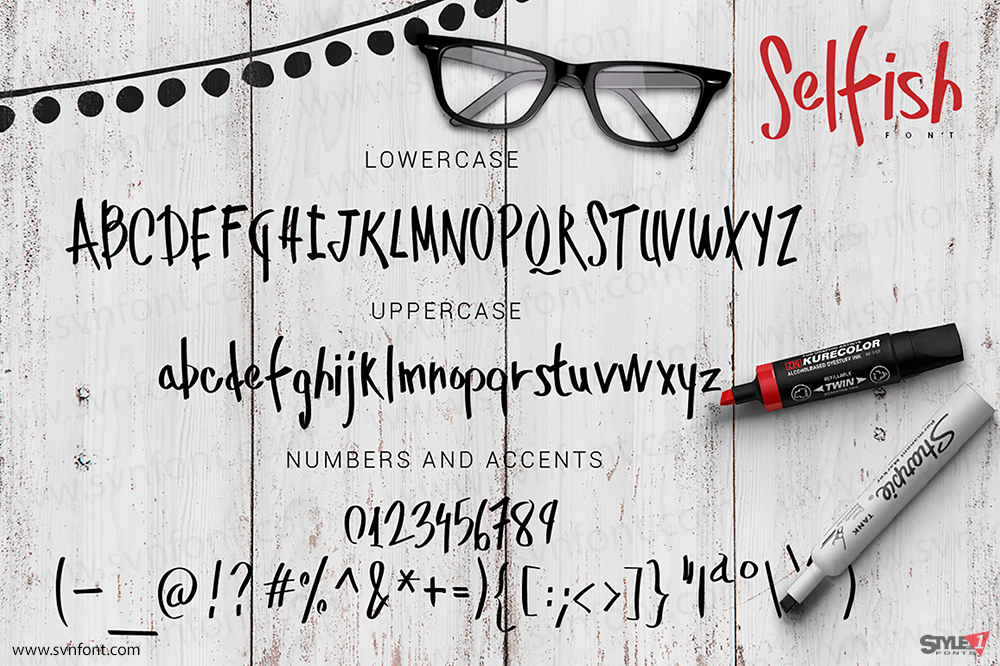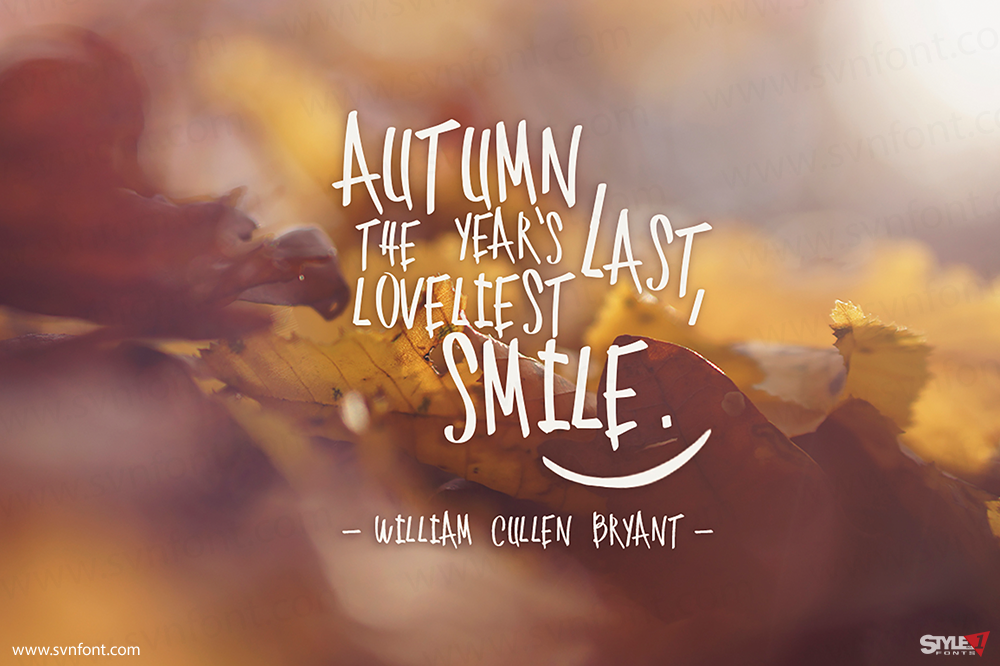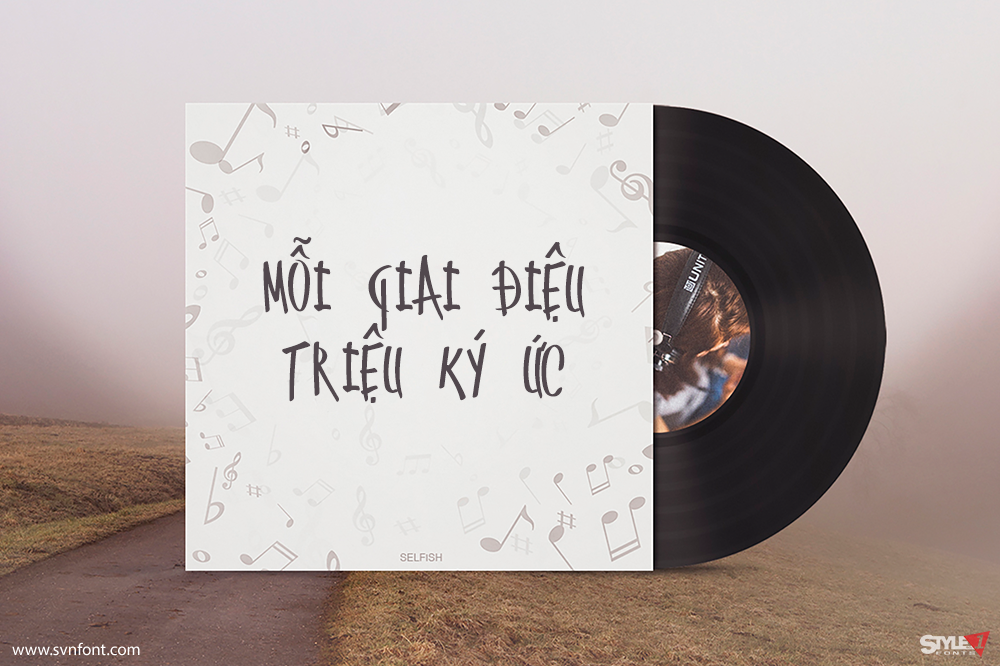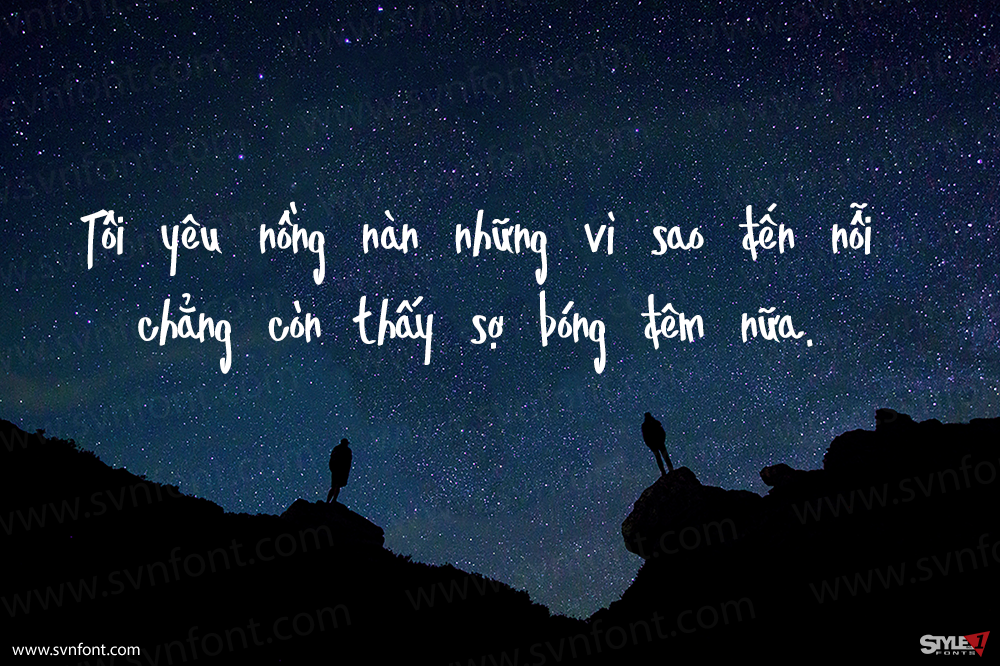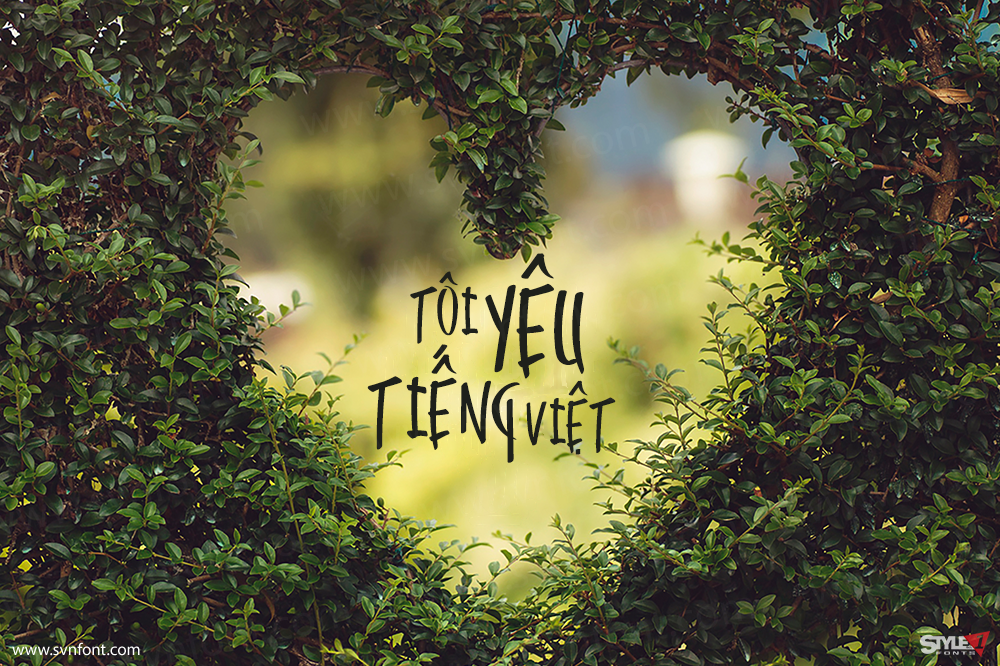
Selfish, một display font (font chữ hiển thị) mô phỏng kiểu chữ viết bằng bút dạ, với mỗi dấu tiếng Việt được tách biệt tạo sự tự nhiên và độc đáo. Font thích hợp cho các thiết kế về poster, bìa sách, trang trí…
Nhà thiết kế: PereEsquerr
Nhà phát hành: PereEsquerr